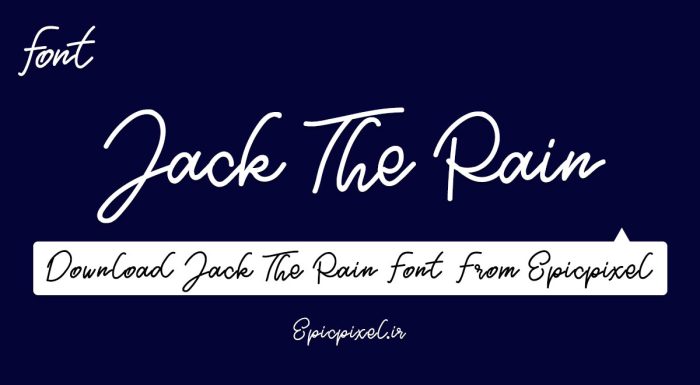
| ⭐ مجموعه فونت | دانلود فونت انگلیسی جک باران Font Jack The Rain جک د رین واش Jack The Rainswash |
| ⭐ توضیحات | معرفی «Jack the Rain»، یک فونت اسکریپت جذاب که ترکیبی از ظرافت و سبک دستنویس تک خطی است. این فونت برای پروژه هایی که نیاز به کمی پیچیدگی و احساس شخصی و دست ساز دارند عالی است. “Jack the Rain” با ویژگی swash خیره کننده خود، ظاهری زیبا و ظریف به طرح های شما می بخشد.
فونت “Jack the Rain” دارای حروف روان و صاف است که زیبایی بی دردسر خط دست نوشته را منعکس می کند. هر ضربه ثابت و یکنواخت است و باعث ایجاد حس تعادل و هماهنگی می شود. سبک تک خطی آن یک پیچ و تاب مدرن میافزاید و به متن شما ظاهری تمیز و امروزی میدهد. |